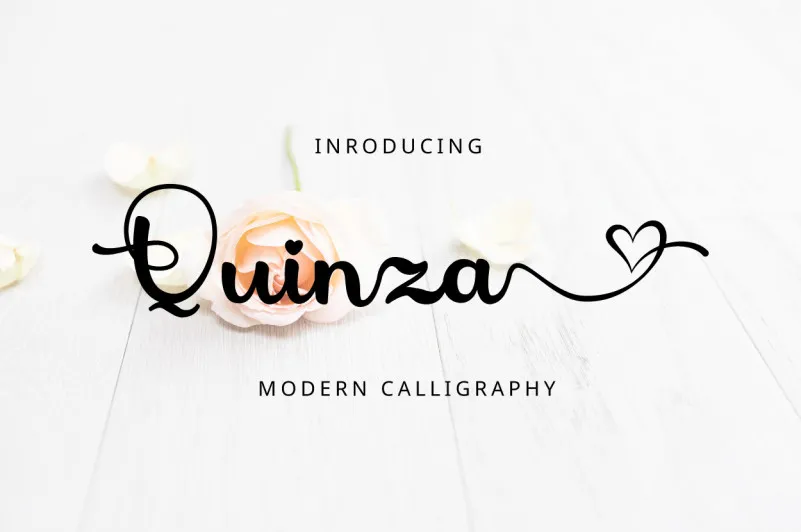
Quinza Script Font – Download Grátis
Descubra a beleza única das escritas artesanais na fonte Quinza Script, criada pelo talentoso designer sugiharto1790. Este fonte é uma paixão do mundo do design, fornecendo um toque de elegância e personalização para seus projetos digitais. Com a sua linhas delicadas e detalhes sofisticados, Quinza Script oferece uma experiência visual incrível em qualquer projeto. Seja criando materiais para o design gráfico ou para a publicidade, a Quinza Script é ideal para tornar suas obras únicas ainda mais especiais. Esta fonte é perfeita para quem valoriza não apenas a funcionalidade de um tipo de letra mas também sua capacidade de deixar seu trabalho com uma personalidade e arco inconfundíveis. Instale-a agora na sua máquina, e junte-se à incrível comunidade que já se tornou fã desta fonte.